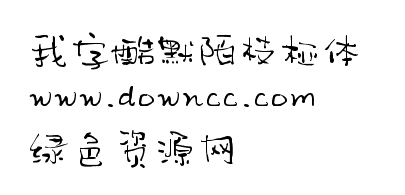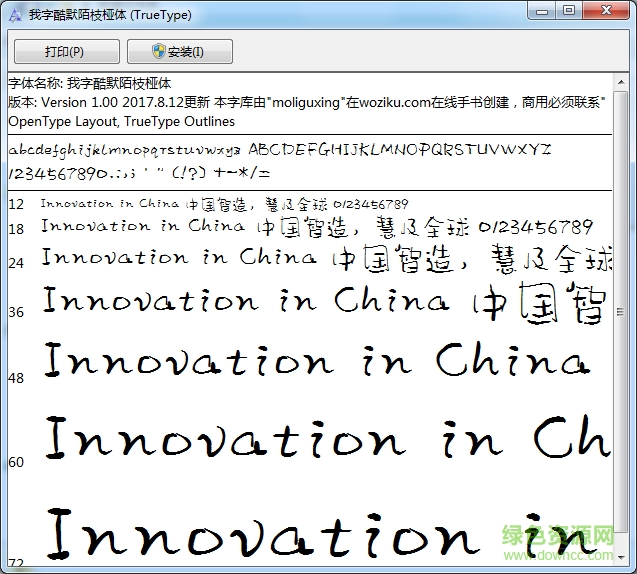
我字酷默陌枝椏體是一款水墨般清淺秀氣的字體,有我字庫推出,采用了手寫體的風(fēng)格,給人恣意灑脫之感,喜歡的朋友來綠色資源網(wǎng)即可免費(fèi)下載哦!
默陌枝椏體采用水墨書寫風(fēng)格,點(diǎn)劃看似隨意,卻保持疏密有致,通過運(yùn)筆節(jié)奏塑造線條粗細(xì)和節(jié)點(diǎn),呈現(xiàn)出一種枯枝藤蔓的造型感,營造出清雅的禪宗意境,特別適用于極簡風(fēng)格海報(bào)、插畫等媒介的配字。